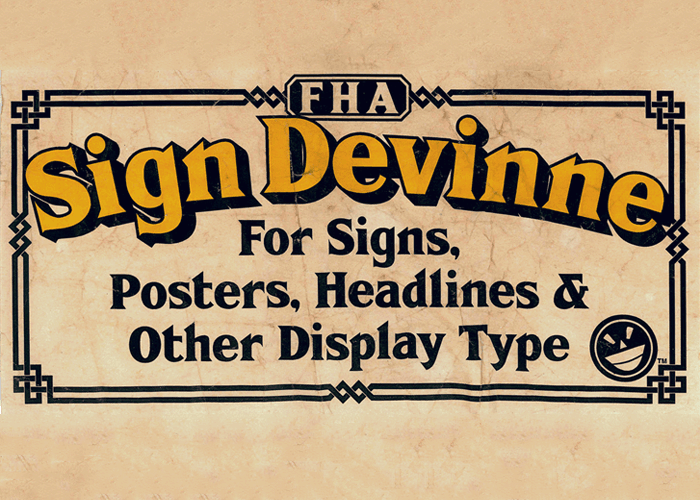
FHA Sign DeVinne é uma fonte Serif que reúne a riqueza tipográfica dos retrabalhos inspirados no trabalho detilhado e apaixonado do artesão de pintura de sinais, F. H. Atkinson. Esta família de fontes mantém o caráter sofisticado e elegante da serif tradicional, mas incorpora elementos modernos que tornam-a ideal para design gráfico atual. Seu designer, Hamilton, preserva os detalhes exatos do original enquanto adiciona ares de frescura ao entrelaçar linhas e espaçamentos cuidadosamente para criar um resultado fluido e elegante em qualquer projeto. Esta fonte oferece uma mistura perfeita entre o passado e o presente. Perfeito para revistas, sites corporativos ou qualquer obra que exigir um toque de sofisticação, FHA Sign DeVinne é uma escolha ótima para designers buscas aperfeiçoamento na tipografia. Suas linhas afiadas e acabamentos cuidadosos garantem a qualidade e estética duradoura necessárias em qualquer projeto gráfico que você esteja iniciando.